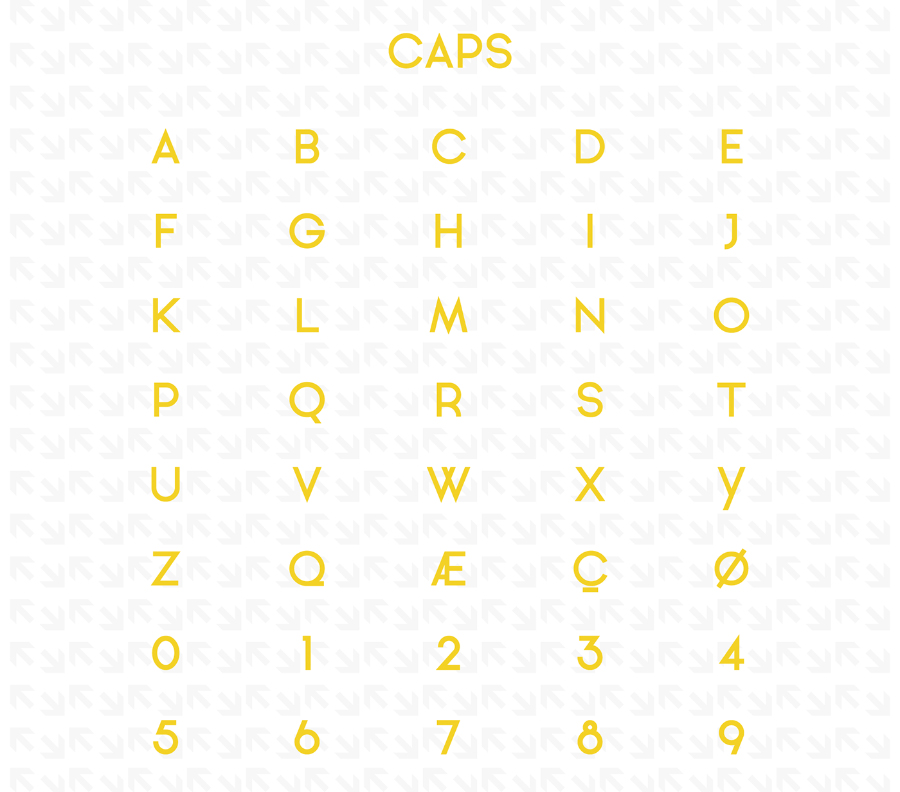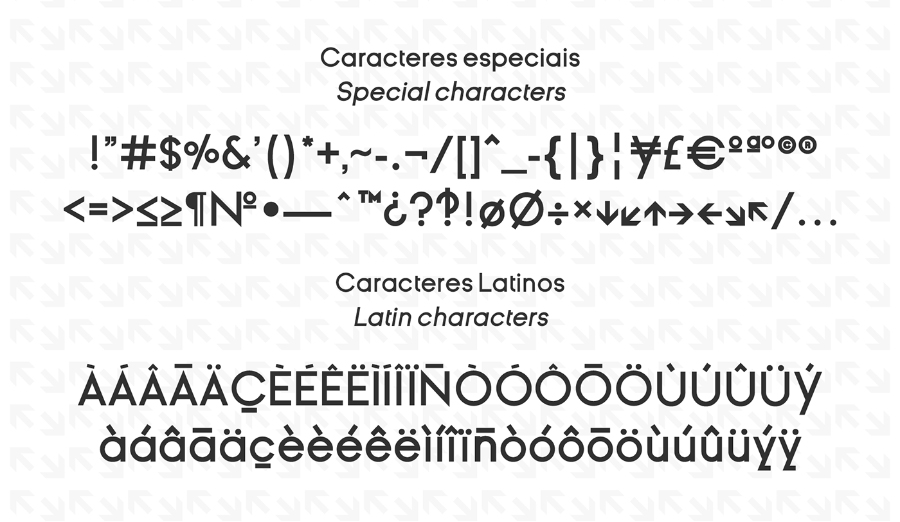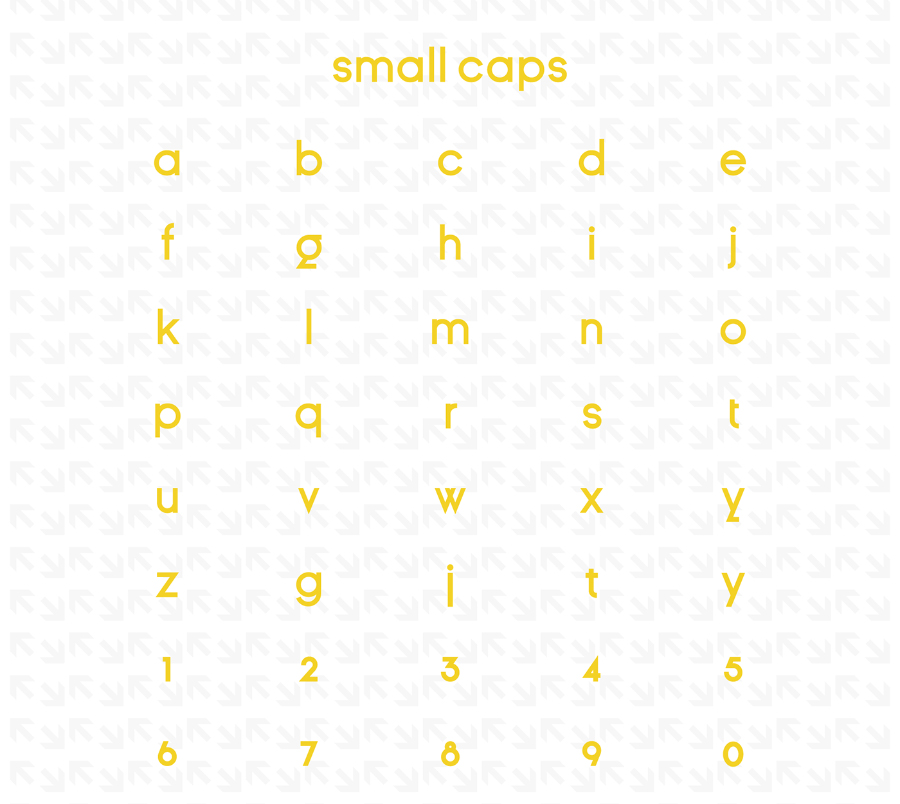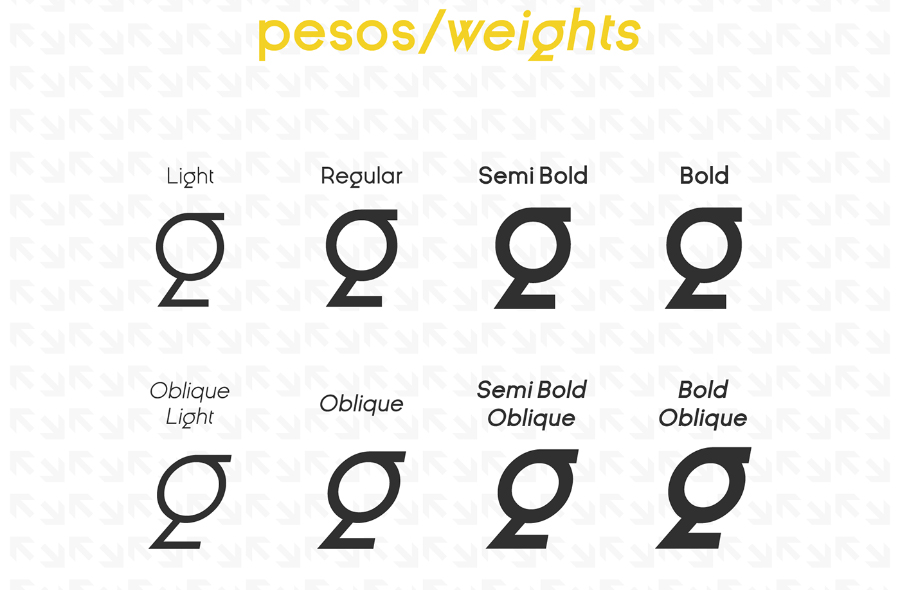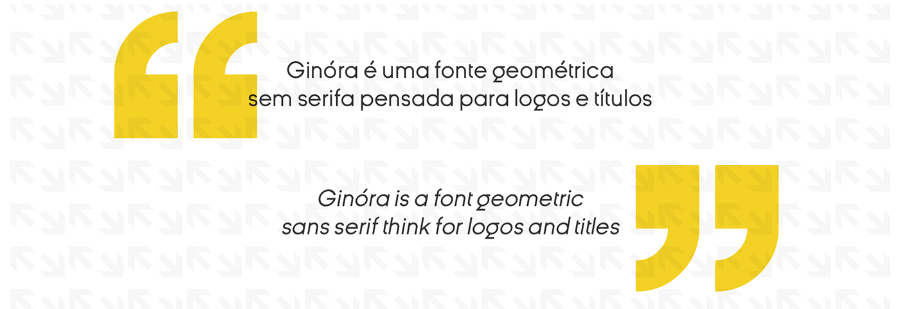
Ginora Sans免费TypeFamily
Ginora Sans Free TypeFamily是一种无衬线字体,带有大写字母和O,Q,G,C等字符的整个圆圈。小写字母有长的上升,也有整圆。吉诺拉的特色字母是宽大的大写字母和完整的圆圈。吉诺拉是伟大的社论标题和正文。使用家庭的组合,使其更有趣。